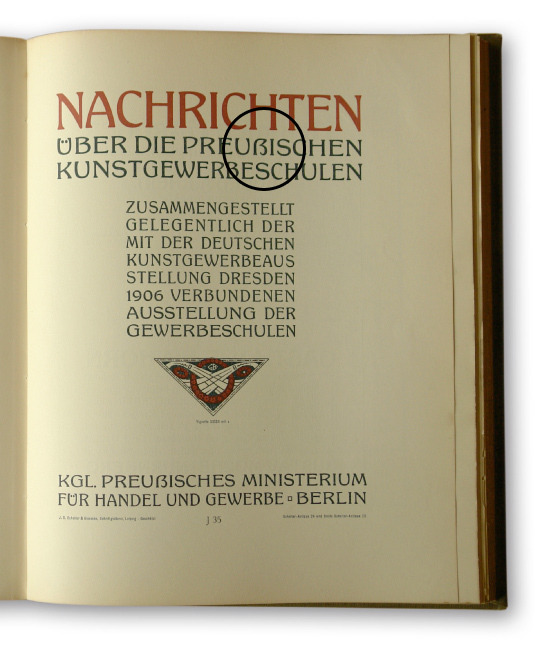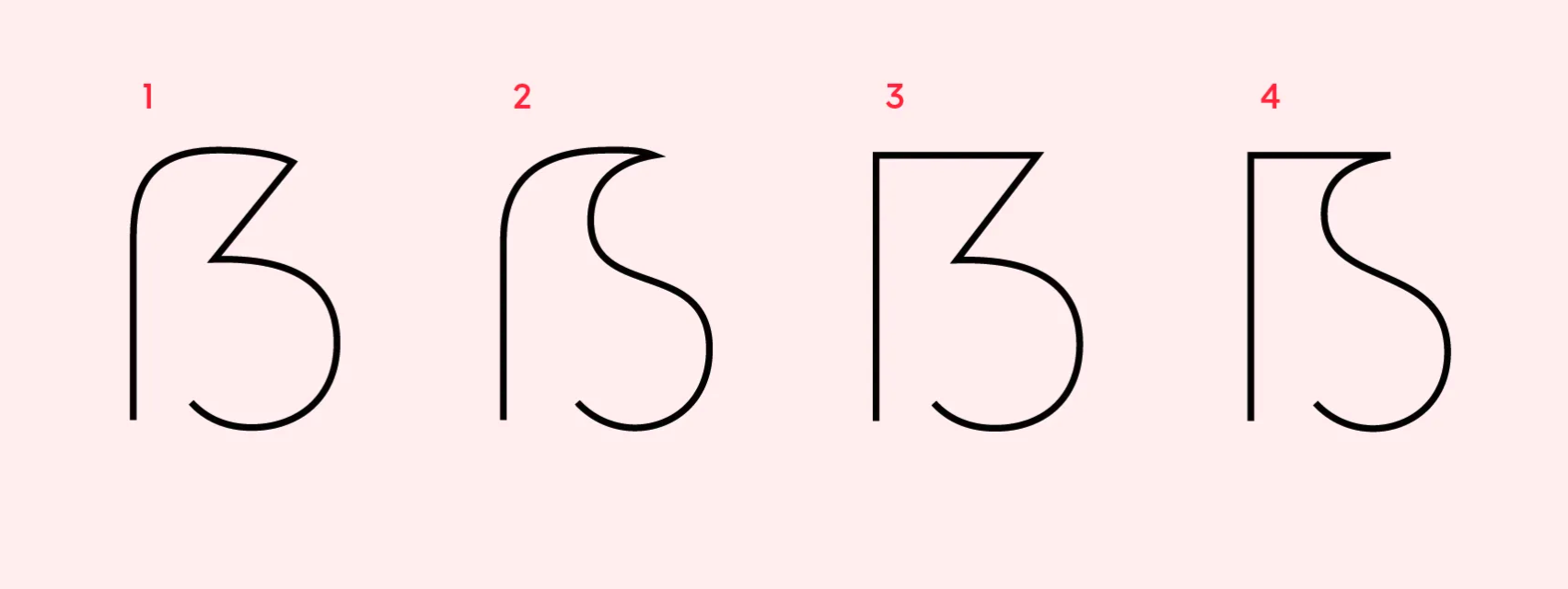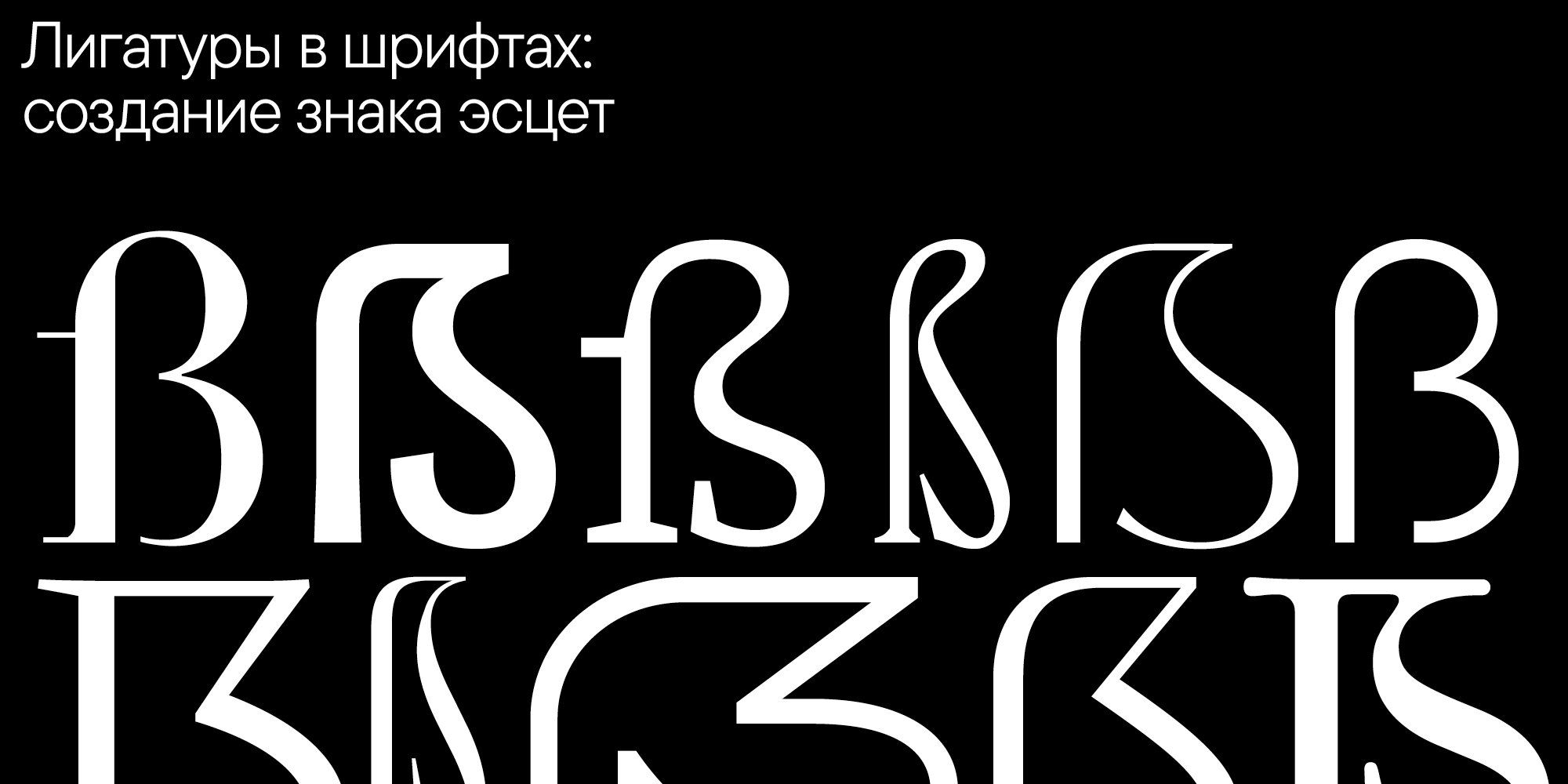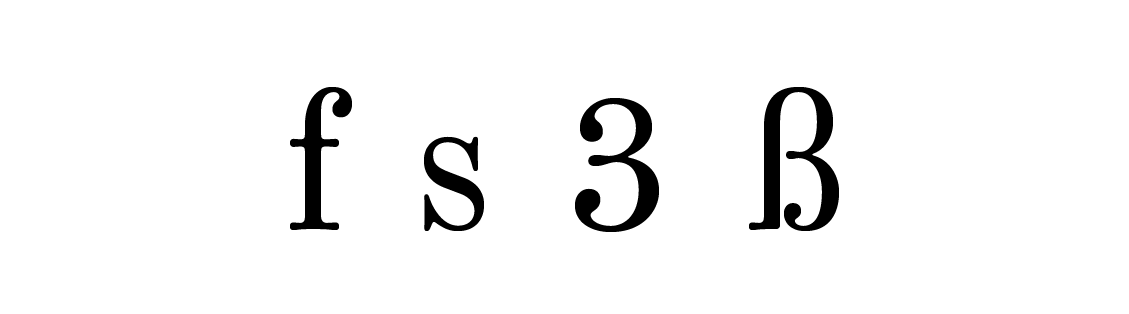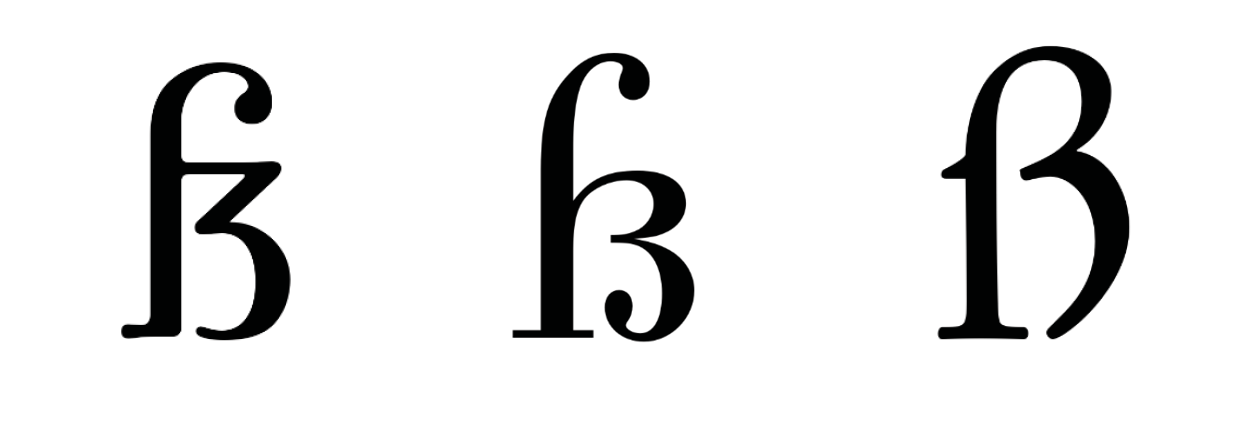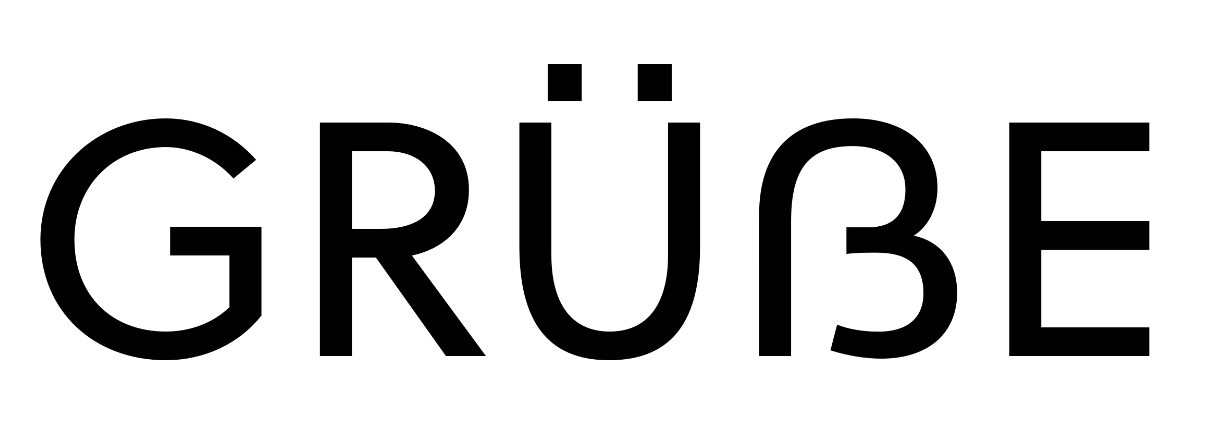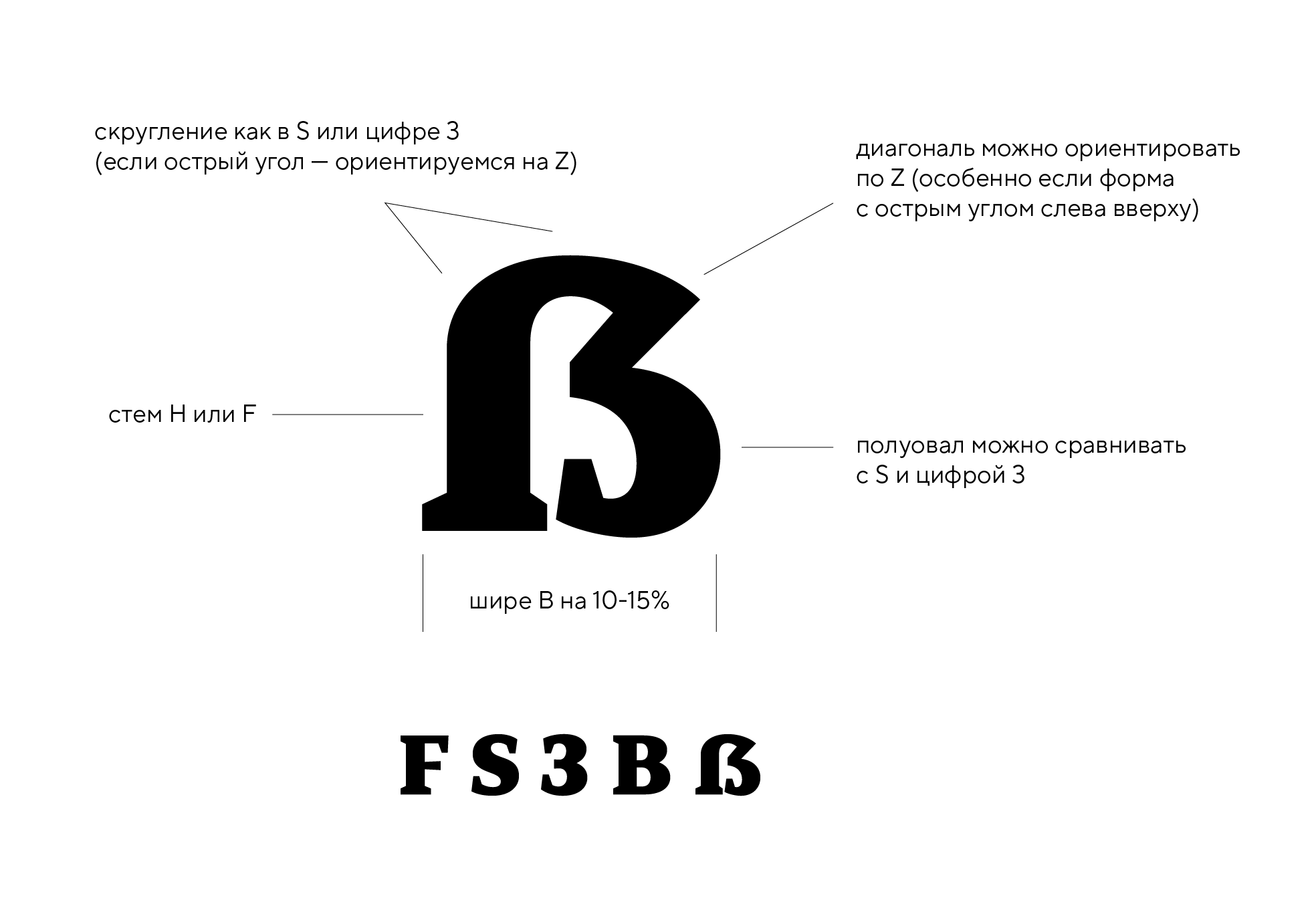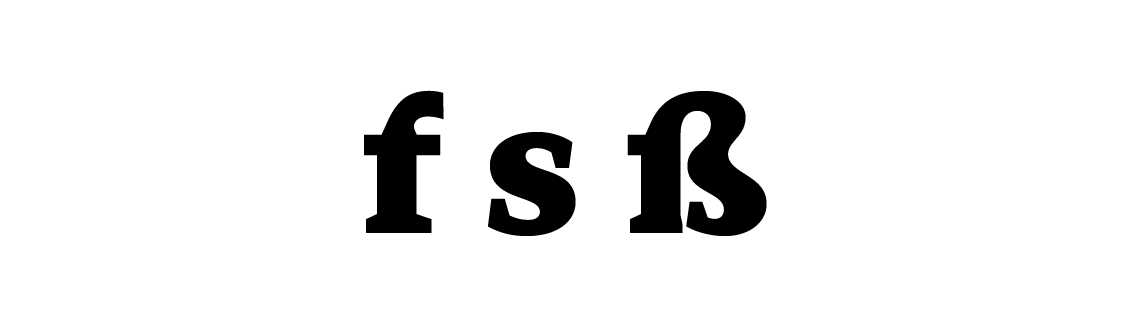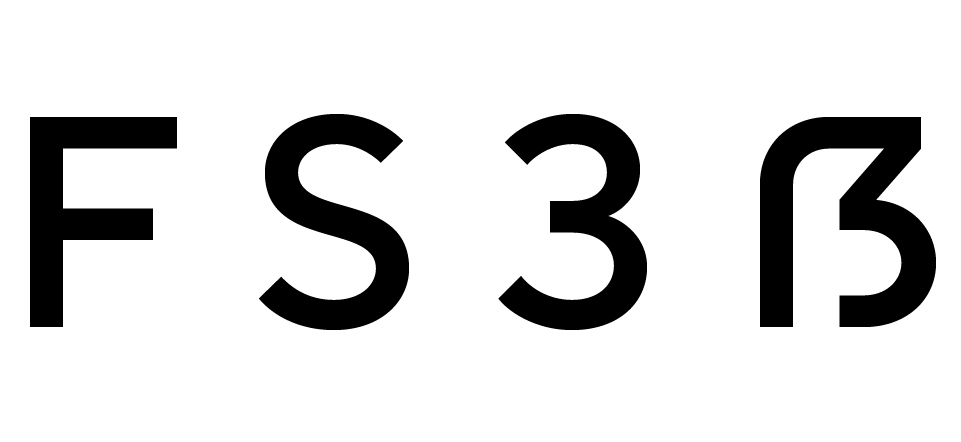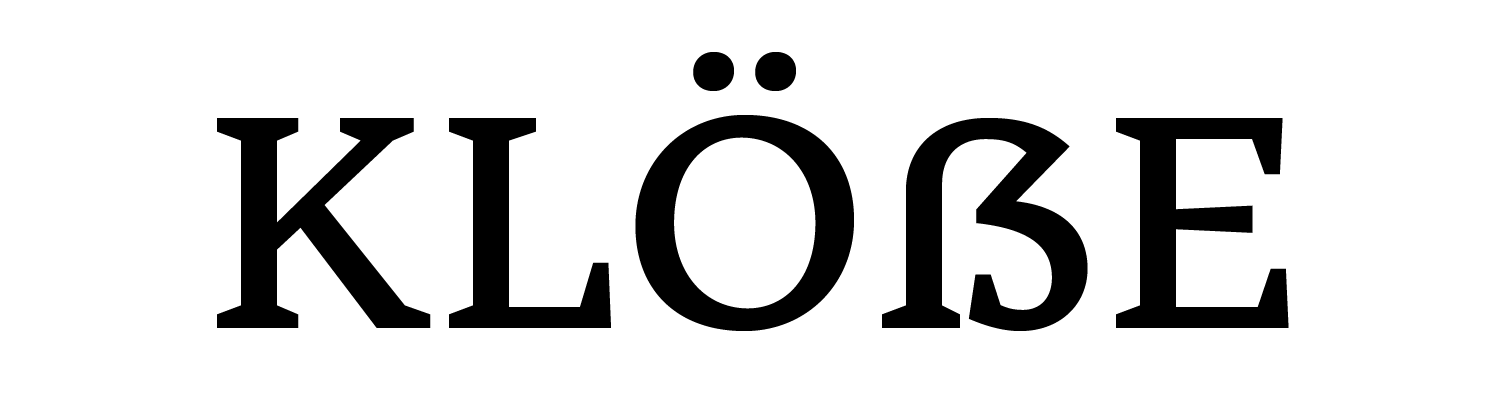
Лигатуры в шрифтах: создание эсцет
Начинающие шрифтовые дизайнеры при расширении знакового состава шрифтов часто сталкиваются с трудностями при рисовании знака эсцет.
В этой статье мы совершим путешествие по истории этого знака, узнаем о его происхождении и роли в современной типографике. Но самое главное — мы расскажем о способах и правилах рисования эсцет при создании собственного шрифта. Первая часть будет посвящена теории, а вторая станет практическим руководством для всех, кто занимается шрифтовым дизайном.
Часть первая. Теоретическая.
Эсцет (или острая s, резкая s) — это знак немецкой орфографии. Раньше использовался в большинстве стран Европы, но сохранился только в немецком языке.
Современные названия знака
С точки зрения дизайна, эсцет — это орфографическая лигатура.
Технически она состоит из ſ (длинной s) и z, из чего следует название — «Eszett».
Распространёнными вариантами являются Eszett и Eszet. В прошлом эти обозначения не использовались в качестве термина, скорее передавали звучание двух букв.
Эсцет часто называют «scharfes S», то есть, в буквальном переводе, острой буквой s. Чихольд в книге «Образцы шрифтов» разъясняет, что соединение ſz в этой букве-лигатуре — неверно понятое соединение длинной s и концевой круглой s. Если придвинуть длинную s и короткую, то от короткой справа останется только часть, похожая на готическую z. Чем дальше печатники уходили от использования длинной s, тем больше искажался первоначальный смысл этой лигатуры.
Форма знака эсцет чем-то похожа на необычную версию буквы B или на греческую beta. Чтобы лучше понять, почему форма эсцет стала именно такой, погрузимся в историю.
Происхождение эсцет
Рассмотрим левую часть лигатуры — длинную s.
Происхождение эсцет
Minion Pro
Длинная s — это архаичная форма буквы, давно вышедшая из употребления. Из современных символов самым близким по форме является математический знак интеграла. Длинная s произошла от древнеримской скорописной буквы s.
В большинстве печатных работ до 1800 года использовались две формы строчных s. Одна из них — короткая или круглая s, знакомая каждому.
Второй была длинная s, визуально похожая на f без правой части перекладины. У неё сохранена засечка слева, которая встречается в дизайне знака эсцет в современной типографике.
В курсивной форме длинной s левая засечка чаще отсутствует.
Происхождение эсцет
Pica No. 2 William Caslon, Specimen of Printing Types, London, 1766.
Печатники первых шрифтов, основанных на готическом письме, следовали установившимся правилам использования начальных и средних длинных s и конечных коротких s.
Однако первые авторы гуманистического письма пользовались только длинными буквами. Некоторые печатники, вдохновившись тенденциями гуманистического письма, начали повторять эту тенденцию, однако вскоре отказались от этой идеи. «Готическое» использование начальных и средних длинных и конечных коротких s стало правилом печати до конца XVIII века.
Длинная s часто перекрывала соседние символы, в таких случаях могли заменить длинную s на короткую. Этот приём использовался перед буквами, с которыми длинная s могла столкнуться. Со временем для подобных комбинаций были созданы специальные лигатурные знаки: sb, sh, si, sk, sl, ss, st, ssi, ssl.
Происхождение эсцет
Фрагмент Weltgericht (1450), предположительно, авторства Гутенберга
В каллиграфии редко использовали длинную s в курсивных формах письма (канцелярский курсив и «итальянский» курсив). Такие свободные принципы отличались от правил печати того времени.
После XVI века длинная s стала постепенно вытесняться. Тенденцию к такому решению задал Джованни Франческо Креши, римский каллиграф-реформатор и учитель. Он редко использовал длинную s в своих работах, и этот стиль перенимали его ученики и последователи.
Длинную s стали реже использовать, и этот подход из каллиграфии перешёл в печать.
Происхождение эсцет
Lanotomia, Rome, 1588. Работа ученика Креши — Людовико Курионе
Первым отказаться от длинной s в своих шрифтах решил Франсуа-Амбруаз Дидо, и его примеру последовали другие печатники. От длинной s отказывались из-за неудобства использования и её формы.
Длинную s можно было встретить в готических шрифтах, например, во фрактуре и швабахере. Большее распространение эти шрифты получили в печати немецкоговорящих стран. Так как большинство книг там печаталось фрактурой, проблем с использованием эсцет и длинной s не возникало.
Однако отказ печатников от длинной s повлиял и на немецкое книгопечатание, ведь римские шрифты становились популярны. Например, в в 1789 году Иоганн Фридрих Унгер единично обрезал длинную s для печати книги Гете «Римский карнавал» в стиле шрифта Дидо. Так у него появилась возможность набрать в тексте эсцет.
В последующем печатники будут либо вырезать знак ſs для немецкого языка в стиле шрифтов Дидо, либо использовать сочетание ss.